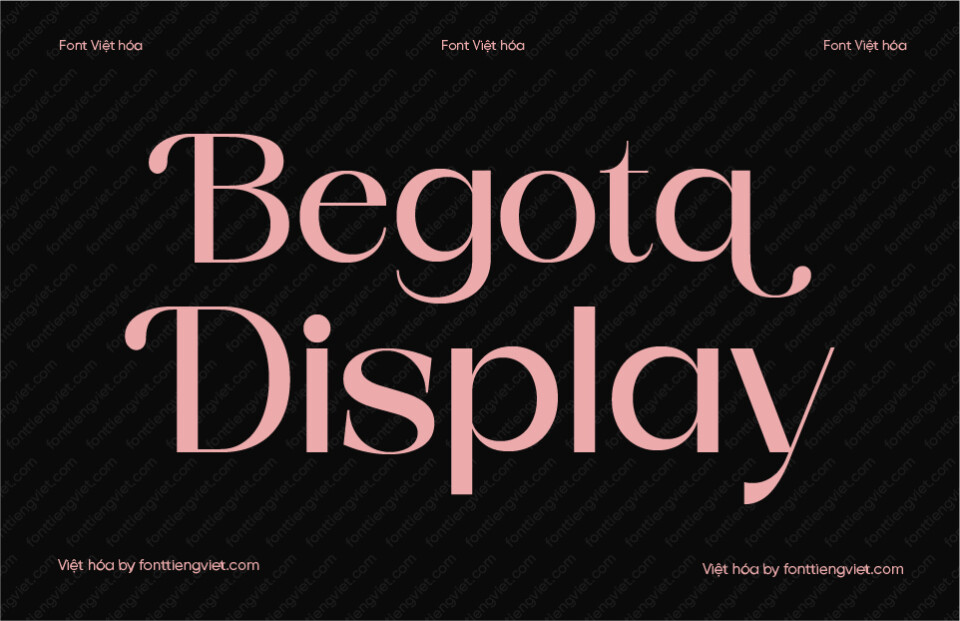
Font Việt hóa 1FTV VIP Begota Display Regular
Font Việt hóa 1FTV VIP Begota Display Regular – Sự Kết Hợp Hoàn Hảo Giữa Sang Trọng Và Hiện Đại
Giới thiệu về Font Việt hóa 1FTV VIP Begota Display Regular
Trong thế giới thiết kế đồ họa ngày nay, việc lựa chọn một bộ Font Miễn Phí chất lượng luôn là ưu tiên hàng đầu của các nhà sáng tạo. Đặc biệt, bộ Font Việt hóa 1FTV VIP Begota Display Regular đã nhanh chóng trở thành tâm điểm chú ý nhờ phong cách thiết kế độc đáo và đầy cuốn hút. Đây không chỉ đơn thuần là một kiểu chữ, mà còn là công cụ đắc lực giúp truyền tải thông điệp một cách tinh tế và chuyên nghiệp nhất. Begota Display mang trong mình hơi thở của sự hiện đại, đan xen với những đường nét cổ điển tạo nên một tổng thể hài hòa và đẳng cấp cho mọi tác phẩm thiết kế từ in ấn đến kỹ thuật số.
Đặc điểm nổi bật của Font Việt hóa 1FTV VIP Begota Display Regular
Thiết kế thanh lịch và tỉ mỉ
Điều làm nên sự khác biệt của Font Việt hóa 1FTV VIP Begota Display Regular chính là cấu trúc chữ cái được chăm chút đến từng chi tiết nhỏ nhất. Với các nét thanh nét đậm tương phản rõ rệt, bộ font này tạo ra một nhịp điệu thị giác mạnh mẽ, giúp người xem dễ dàng bị thu hút ngay từ cái nhìn đầu tiên. Các ký tự được thiết kế với độ mở rộng vừa phải, tạo cảm giác thoáng đãng và dễ đọc, ngay cả khi được sử dụng ở kích thước lớn trong các tiêu đề quan trọng.
Khả năng hiển thị tiếng Việt hoàn hảo
Một trong những nỗi lo lớn nhất của các designer tại Việt Nam là lỗi hiển thị dấu tiếng Việt. Tuy nhiên, với phiên bản Font Việt hóa 1FTV VIP Begota Display Regular, mọi vấn đề về dấu câu đã được xử lý triệt để. Các dấu thanh được đặt ở vị trí cân đối, không làm mất đi cấu trúc nguyên bản của font chữ, đảm bảo tính thẩm mỹ cao nhất cho các văn bản thuần Việt. Điều này giúp bộ font trở nên cực kỳ hữu dụng cho các dự án thiết kế nội địa đòi hỏi sự chỉn chu và chuẩn mực cao.
Ứng dụng thực tế của bộ font Begota Display
Thiết kế thương hiệu và bao bì
Nhờ vẻ ngoài sang trọng, Font Việt hóa 1FTV VIP Begota Display Regular là lựa chọn lý tưởng cho các dự án nhận diện thương hiệu cao cấp như mỹ phẩm, thời trang hoặc trang sức. Khi xuất hiện trên bao bì sản phẩm, font chữ này không chỉ cung cấp thông tin mà còn khẳng định giá trị và đẳng cấp của nhãn hàng trong mắt người tiêu dùng.
Truyền thông xã hội và tiêu đề bài viết
Trong kỷ lục số, việc làm nổi bật tiêu đề trên các nền tảng như Facebook hay Instagram là vô cùng quan trọng. Sự độc đáo của Begota Display Regular giúp các banner quảng cáo hoặc ảnh bìa trở nên nghệ thuật hơn, giúp thông điệp của bạn nổi bật giữa hàng ngàn nội dung khác trên bảng tin của người dùng.
Kết luận về Font Việt hóa 1FTV VIP Begota Display Regular
Tóm lại, việc sở hữu bộ Font Việt hóa 1FTV VIP Begota Display Regular trong thư viện tài nguyên thiết kế là một bước đi thông minh cho bất kỳ ai yêu cái đẹp. Bộ font này không chỉ đáp ứng tốt về mặt kỹ thuật mà còn mang lại giá trị cảm xúc lớn lao cho người xem. Nếu bạn đang tìm kiếm một giải pháp Typography chuyên nghiệp, đừng bỏ lỡ cơ hội trải nghiệm Font Miễn Phí, Font Việt Hóa, Font Việt hóa 1FTV VIP Begota Display Regular để biến những ý tưởng sáng tạo của mình thành những tác phẩm nghệ thuật thực thụ ngay hôm nay.